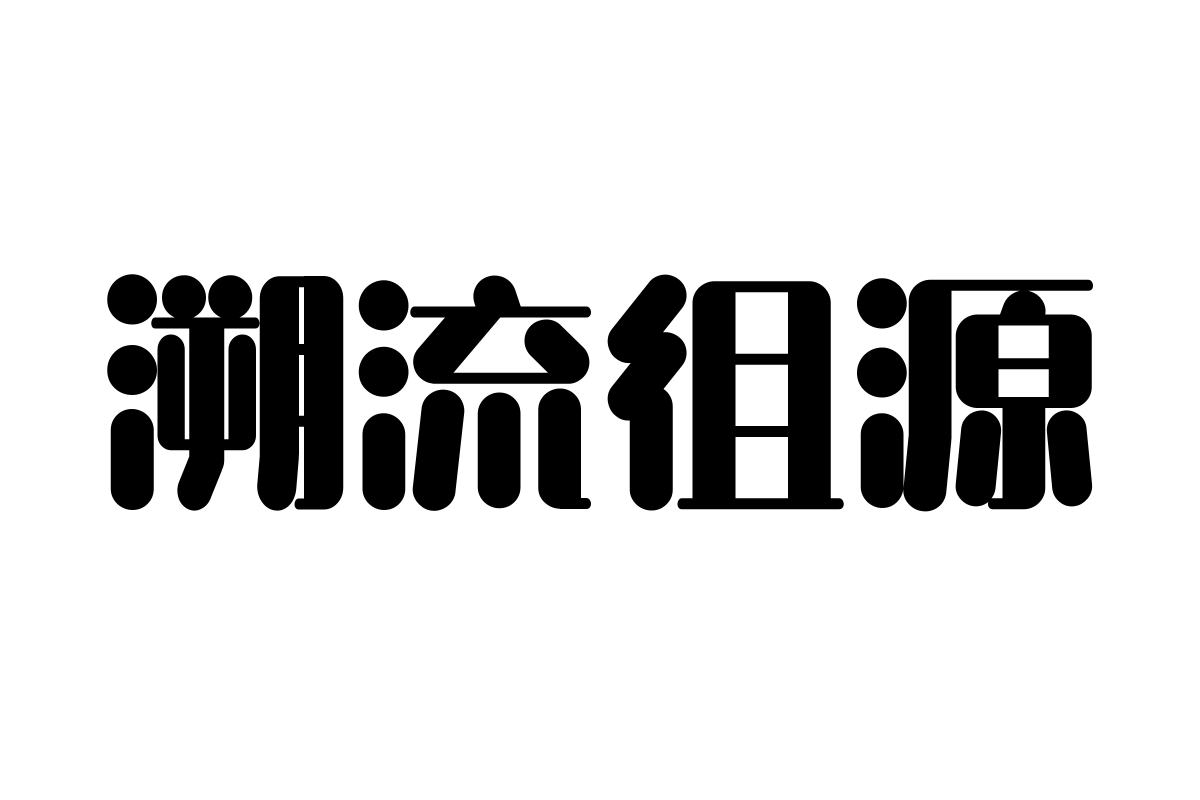
汉仪晓波熊猫体 W 是一款专为中文字体设计的字体,具有独特的设计风格和丰富的表现力。这款字体采用了熊猫形象的元素,使得整体视觉效果更加生动可爱。
该字体的笔画流畅自然,线条粗细适中,适合用于各种文字设计场景,如标题、正文、广告、海报等。同时,汉仪晓波熊猫体 W 还具有较强的可读性和辨识度,适用于需要突出个性和创意的文字排版。
此外,这款字体还支持多种字号和字形选择,可以根据不同的设计需求进行调整和搭配,以满足不同场合和风格的要求。无论是用于网页设计、杂志排版还是其他媒体内容,汉仪晓波熊猫体 W 都能展现出其独特的魅力。
汉仪晓波熊猫体 W